ダイナフォント年間ライセンス「DynaSmart V」2020年10月新書体情報
文字フォント開発、およびその関連製品の開発・販売・保守を行う、ダイナコムウェアは、ダイナフォント年間ライセンス「DynaSmart V」「DynaSmart 教育機関向けプラン」「DynaSmart 学生版」ユーザーに向けて、2020年10月新書体「青花(せいか)ゴシック体」「金剛黒体(こんごうこくたい)コンデンス」、テロップ書体「娥眉(がび)明朝体S」「POPミックスS」を含むダイナフォント112書体を2020年10月19日(月)より提供した。
「DynaSmart V」はWebなどデジタルデザインに最適な「青花ゴシック体」、4種類の横幅×6ウェイトのコンデンス書体の追加でますます使いやすくなる「金剛黒体」、2種類の「テロップ新書体」など、豊富な追加ラインナップ書体で、デザインの可能性をさらに広げていく。
ダイナフォント2020年新書体「青花ゴシック体」
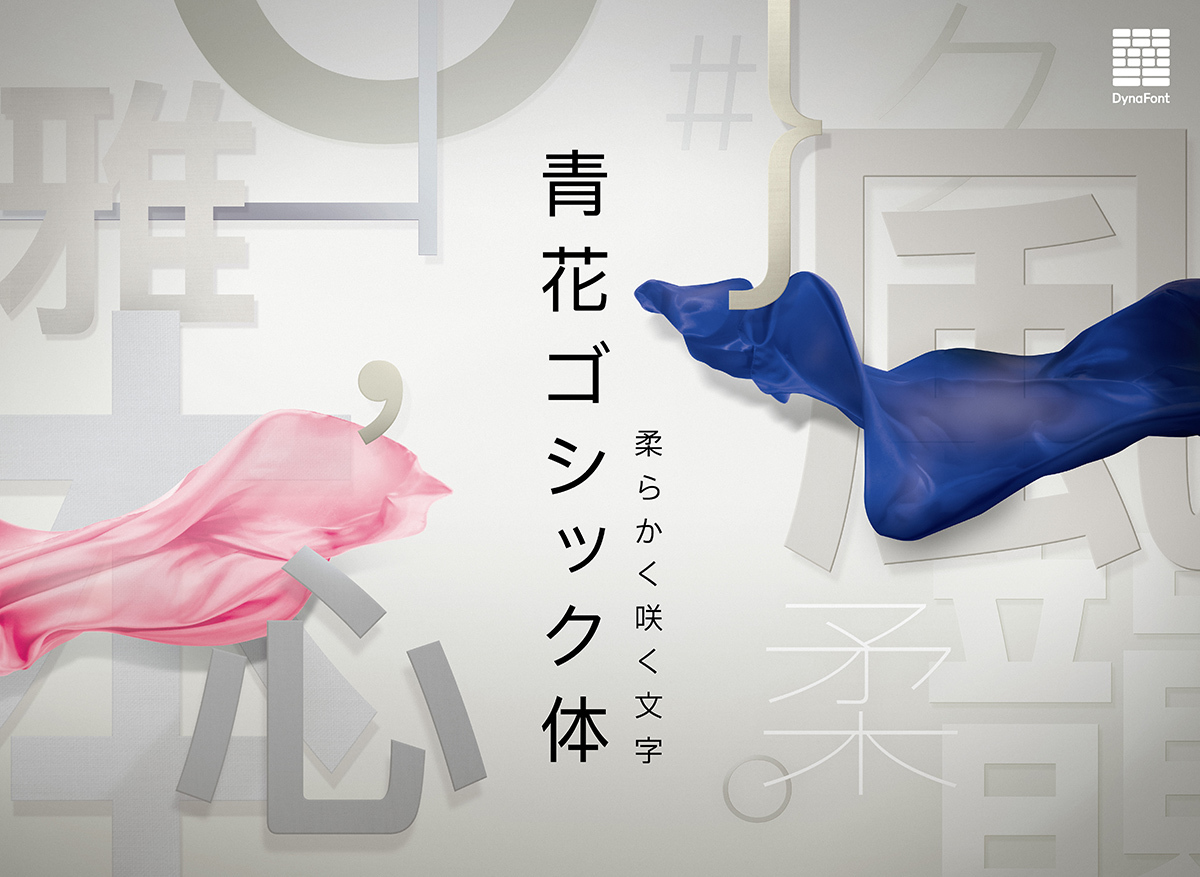
「青花ゴシック体」は、Webなどデジタルデザインで幅広くご使用いただくことを念頭に、シンプルでモダンな雰囲気の字形に広々としたふところ、また、字幅によって落ち着いた印象を与えると共に筆画間の空間を狭めることで、上品なイメージに仕上げたニュートラルなゴシック体。
Webおよびオンスクリーンでのはっきりとした視認性に柔らかい読み心地と7種類のウェイトという機能性を考慮した設計により、見出しから説明文まで幅広く使用できる。
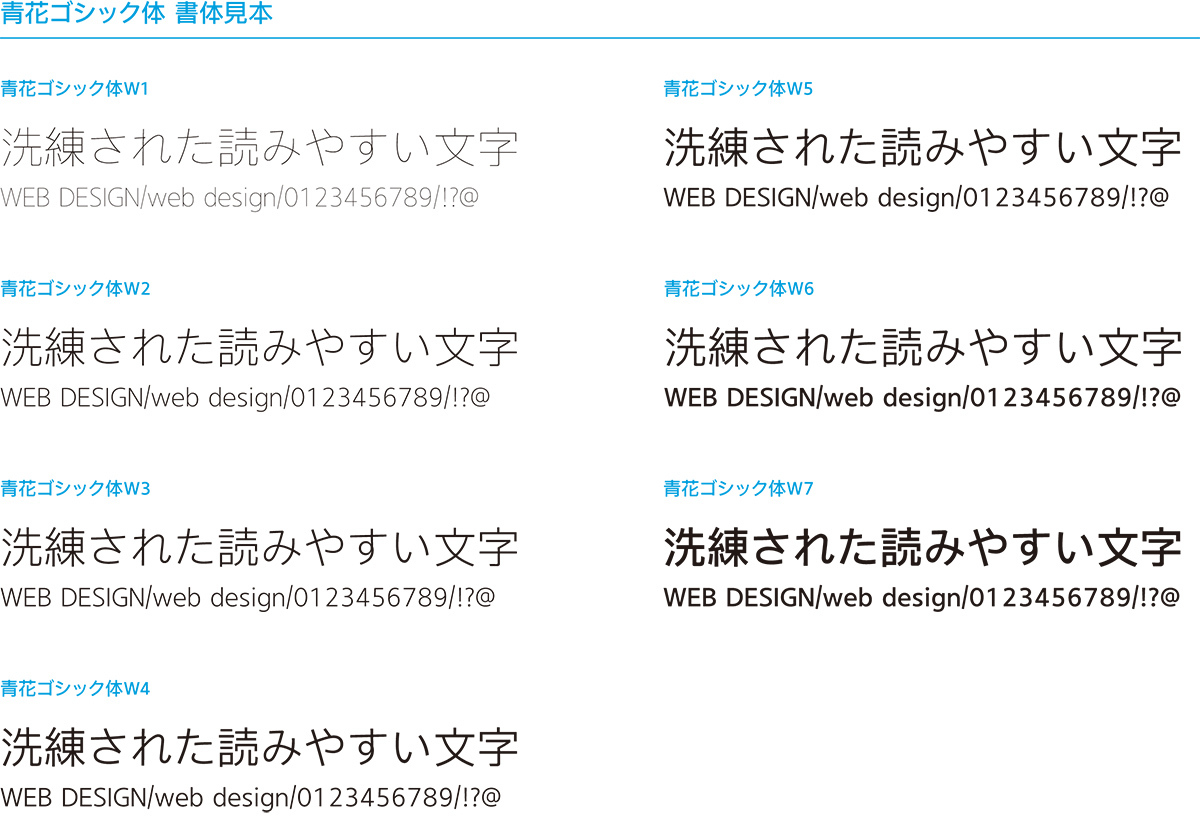
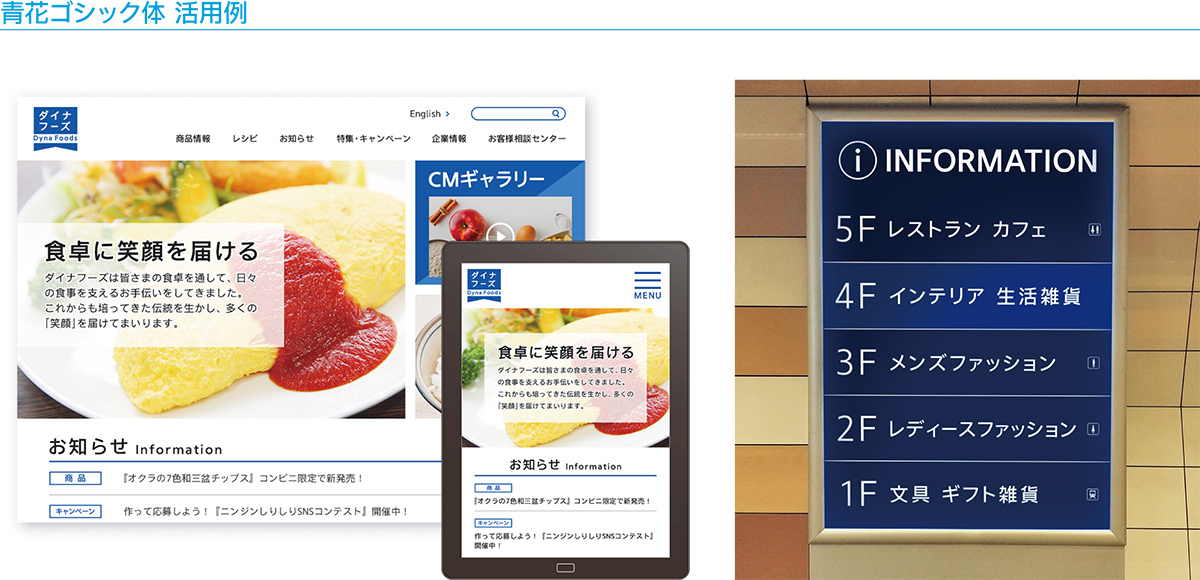
ダイナフォント2020年新書体「金剛黒体コンデンス」
「金剛黒体コンデンス」は、様々な用途に合わせて使用できるように、基準となる金剛黒体から90%、85%、80%、75%の4種類の横幅と6ウェイトで展開するコンデンス書体。
金剛黒体ならではの柔らかな曲線や風通しの良さや、美的センスが随所に感じられるデザインになっている。
滑らかなストロークに、縦線・横線の太さを均一にして構造に安定性を持たせるなど、細部までこだわり、小さなサイズの文字の使用においても高い視認性を保つことができる。
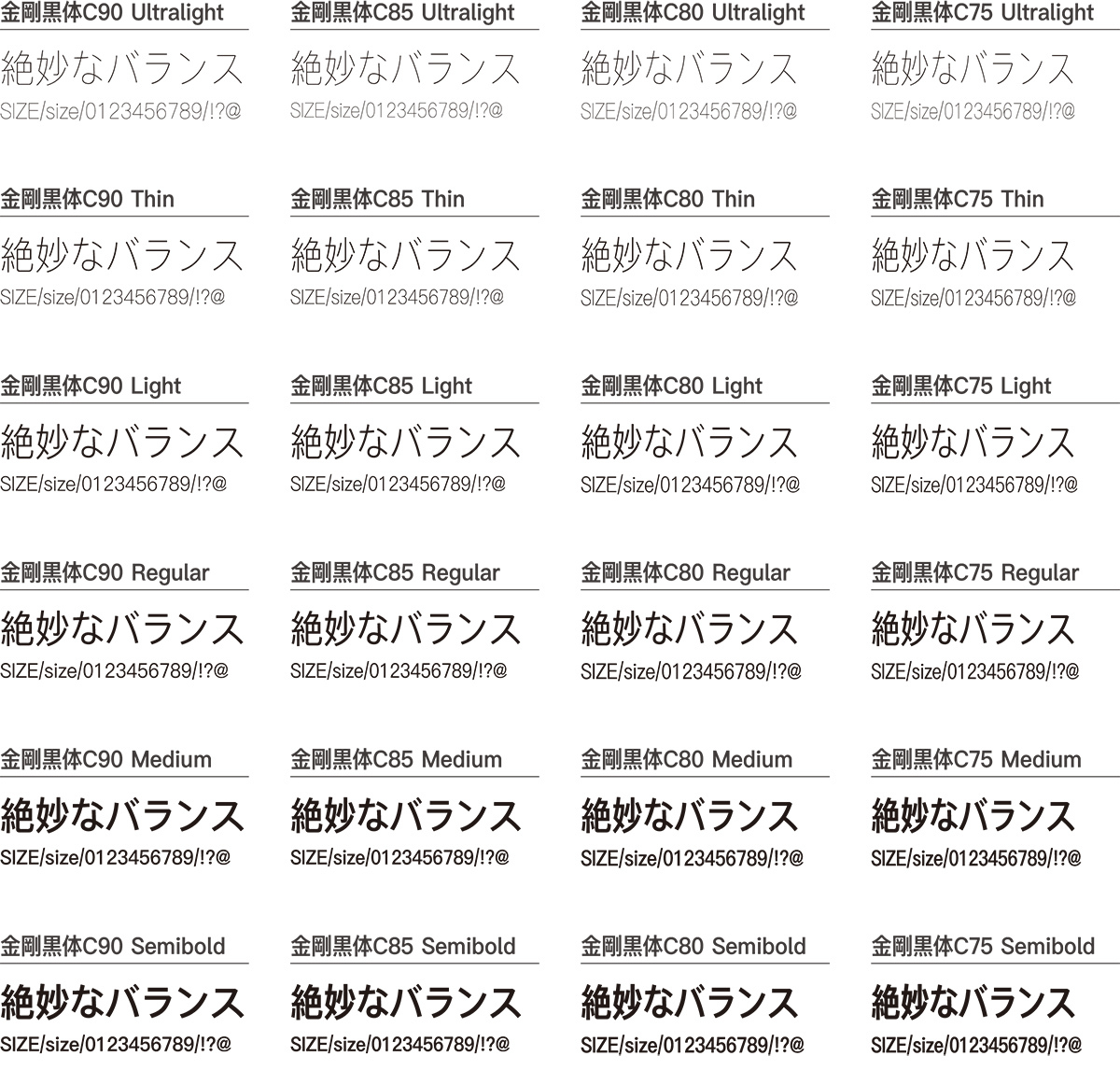
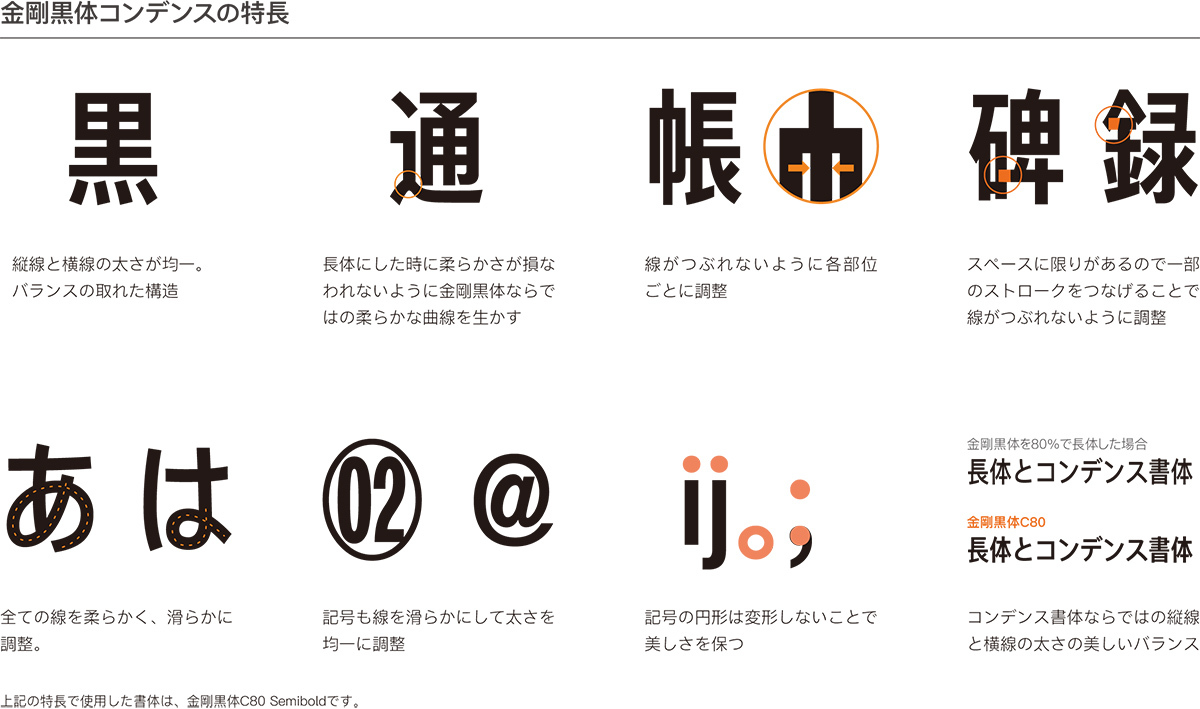
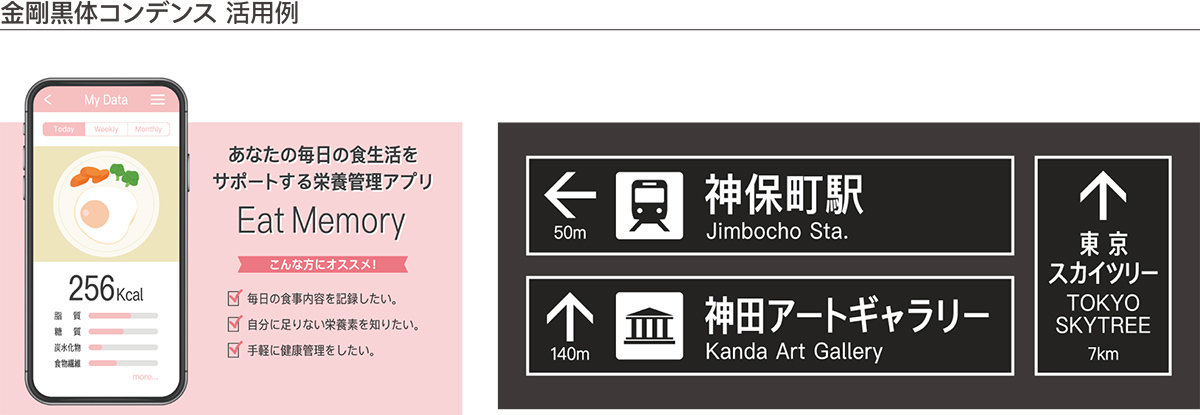
ダイナフォント2020年新書体・テロップ書体「娥眉明朝体S」「POPミックスS」
テロップ書体「娥眉明朝体S」は、細長く弧を描いた眉の形をイメージしたストロークから洗練された女性の柔らかさや優しさを表現した明朝体として開発した人気書体・娥眉明朝体をテロップ表示用に再設計した書体。
テロップ書体「POPミックスS」は、縦画と横画の太さはほぼ均一で旁の右側部分を曲線にし、左側の偏を直線的な切り口にすることでストロークの特徴が際立った端正な雰囲気の中にも遊び心を持ち合わせたPOP系のデザイン書体・POPミックスをテロップ表示用に再設計した書体。
追加される2種類のテロップ書体により、これまで以上に多彩な演出が可能になる。
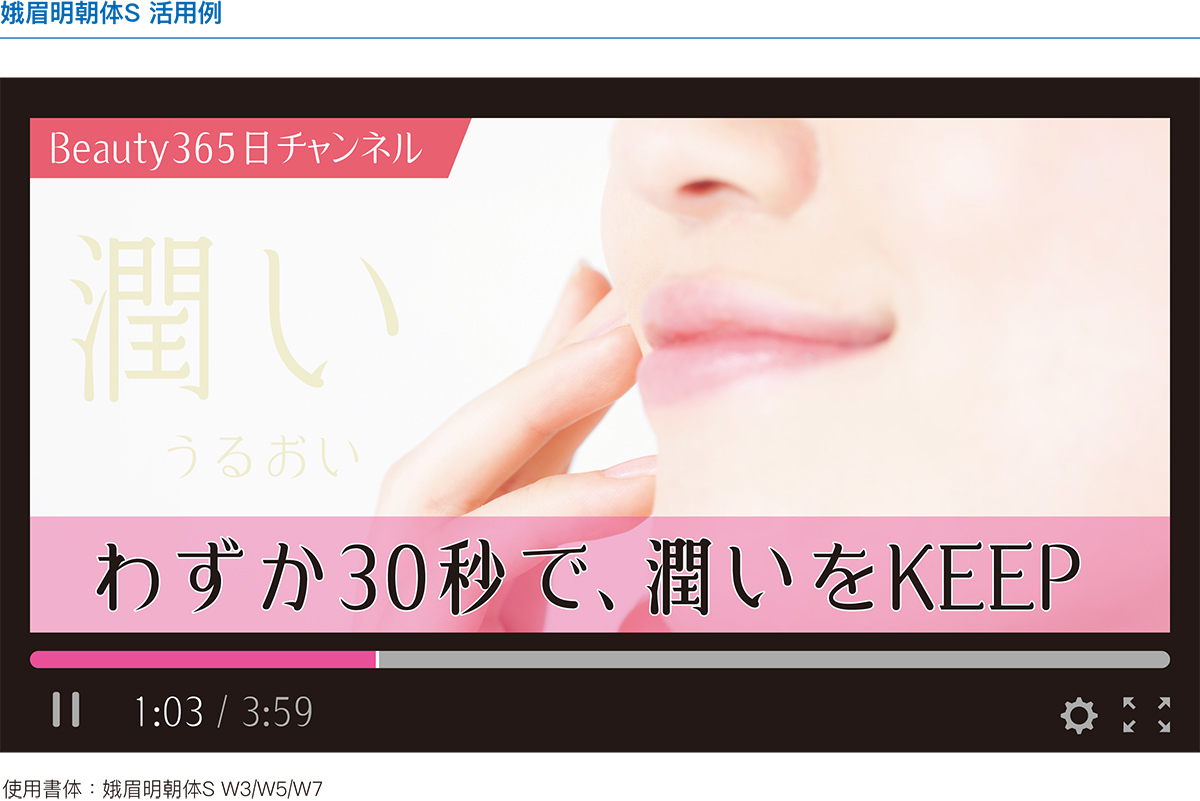
ダイナフォント2020年追加書体「舞風隷書体」
「舞風隷書体」は、伝統的な書道の様式を基に隷書体特有の横長の骨格と波打つような運筆である波磔を取り入れ、力強さの中にも躍動感のある運筆で、伸びやかなはらいと滑らかな提按(上げ、押さえ)といった隷書体の個性を際立たせ、文字の美しさを表現した書体。